Er zijn altijd weer politici die beweren dat onze vrijheid gediend is bij het uitsluiten van anderen die verschillen in uiterlijk, gevoel of geloof. Ze kunnen die anderen gewoon niet verdragen, en gooien gemakshalve de hele groep op één hoop met de weinigen die problemen veroorzaken. Ik snap dat wel, het maakt het leven zoveel gemakkelijker. Zelf heb ik een hekel aan “de” mannen met stropdassen. Ik ben ooit ontslagen door een man met een stropdas, en de grote fraudeurs zijn bijna zonder uitzondering mannen met stropdassen. Allemaal lui die zich niet gedragen volgens onze normen en waarden. Zou ons land beter af zijn als we alle mannen met stropdassen op een lek bootje naar Engeland zouden sturen? Nee, natuurlijk niet. De meeste mannen met stropdassen zijn brave burgers en geen grootschalige oplichters.1
Begin 2024 werd ik er weer behoorlijk misselijk van. Wat de aanleiding precies was weet ik niet meer, we zijn inmiddels een jaar en allerlei waanzin verder. Misschien werd er weer een hoop kabaal gemaakt over “de” moslims, “de” Marokkanen en “de” asielzoekers die de schuld zouden zijn van alles wat hier mis gaat. Of anders kraamde een politicus uit oost of west onzin uit over wokeness of nazisme. Hoe dan ook, ik moest mijn woede en verdriet kwijt en begon aan een poster.
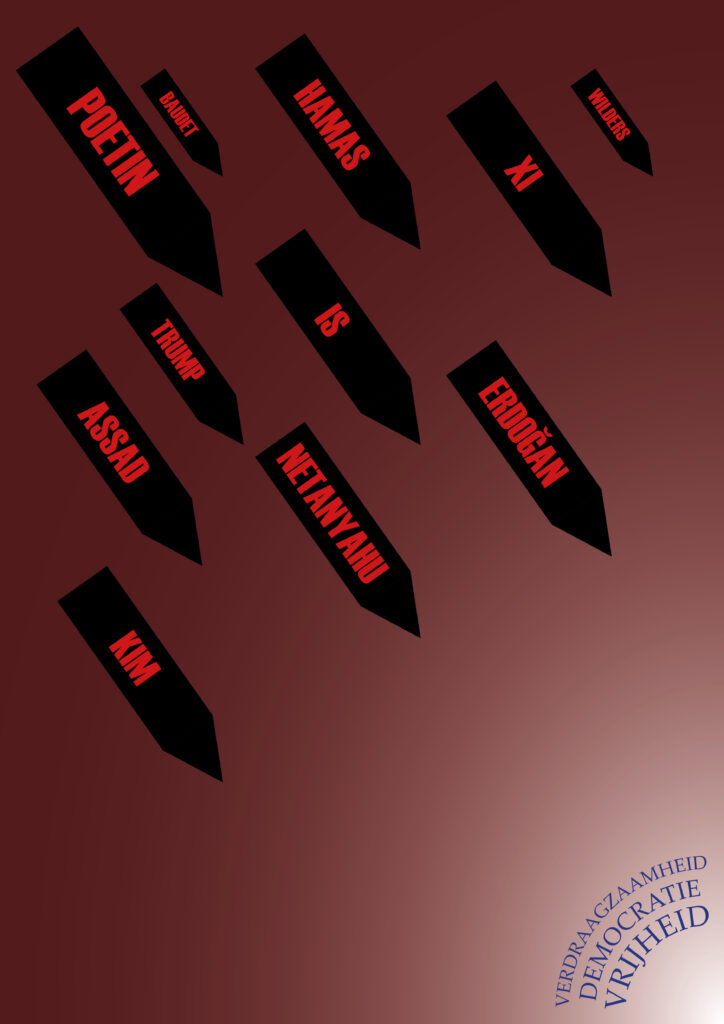
In de eerste versie zie je dat ik de pest heb aan dictators, bijna-dictators en hun vriendjes. Net als Hitler en Mussolini zijn die van nu soms zelfs democratisch gekozen, waarna ze hebben besloten dat ze nooit meer weggaan. Ik heb wel wat getwijfeld wat er op de bommen moet staan. Bijna-dictatorbommen kloppen wel, die bedreigen ons nog, maar actuele dictators als Kim, Poetin, Xi en Assad 2 hadden de vrijheid al verwoest.
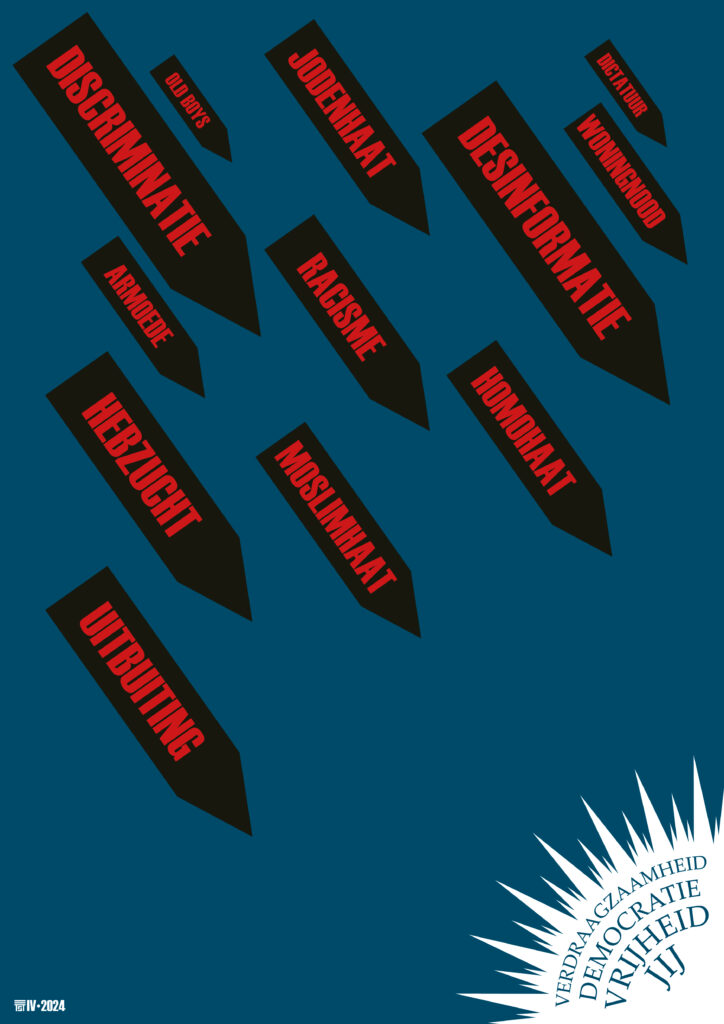
Vandaar een tweede versie met vormen van discriminatie, uitsluiting en ander onrecht op de bommen. We hebben het hier in Nederland allemaal, op de dictatuur na…
De kleur van dit ontwerp is zo dat het kan worden gezeefdrukt in (donker) cyaan en rood. Als je die overlappend afdrukt wordt de kleur zwart. De letter op de bommen is de Haettenschweiler, speciaal vanwege het lelijke woordbeeld. De andere letter is de Palatino.
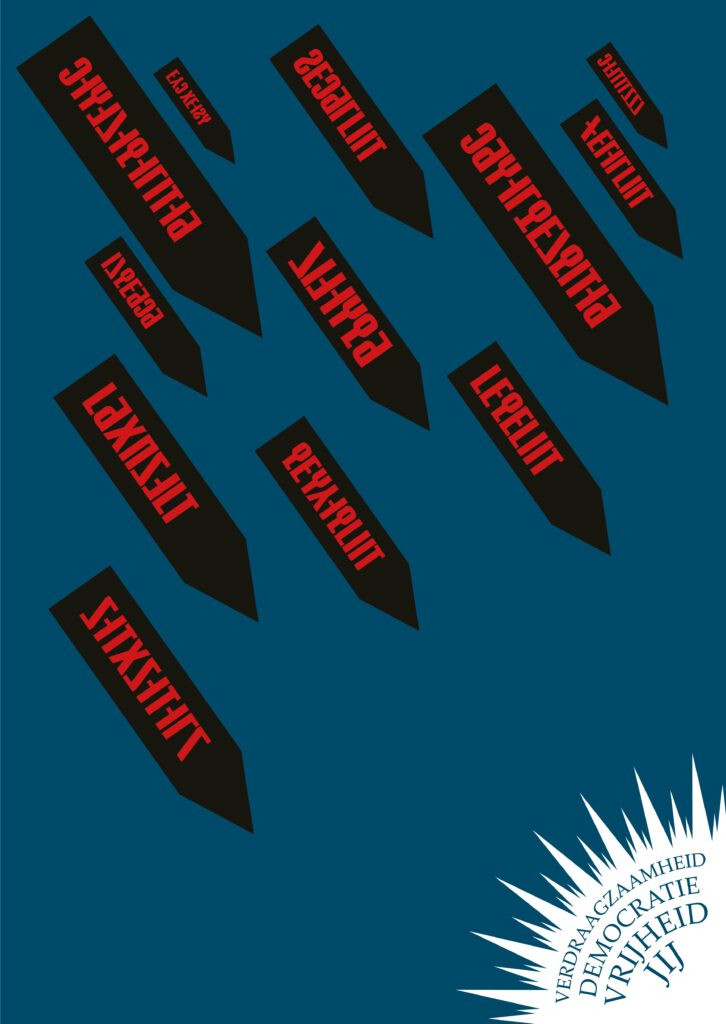
Was dit te concreet, met al die woorden? Moesten de lezers het zelf kunnen bedenken? In juni probeerde ik een versie met onleesbare bommen.
Dat was toch niet zo’n goed idee. Het leek net alsof Armenië onze vrijheid bedreigde.
Ik kwam er niet goed uit totdat de Verenigde Staten werden overgenomen door Trumps kliek …
… en ik een tekst tegenkwam van Martin Niemöller, een Duitse dominee. In 1933 dacht hij nog dat Hitler iets goeds te bieden had, maar geleidelijk aan zag hij in dat de nazi’s niet de gemeenschapsstichters waren die ze beweerden te zijn. Na een preek tegen Hitler in 1937 belandde Niemöller in concentratiekamp Sachsenhausen, en later in Dachau. Hij overleefde de oorlog en overleed in 1984.
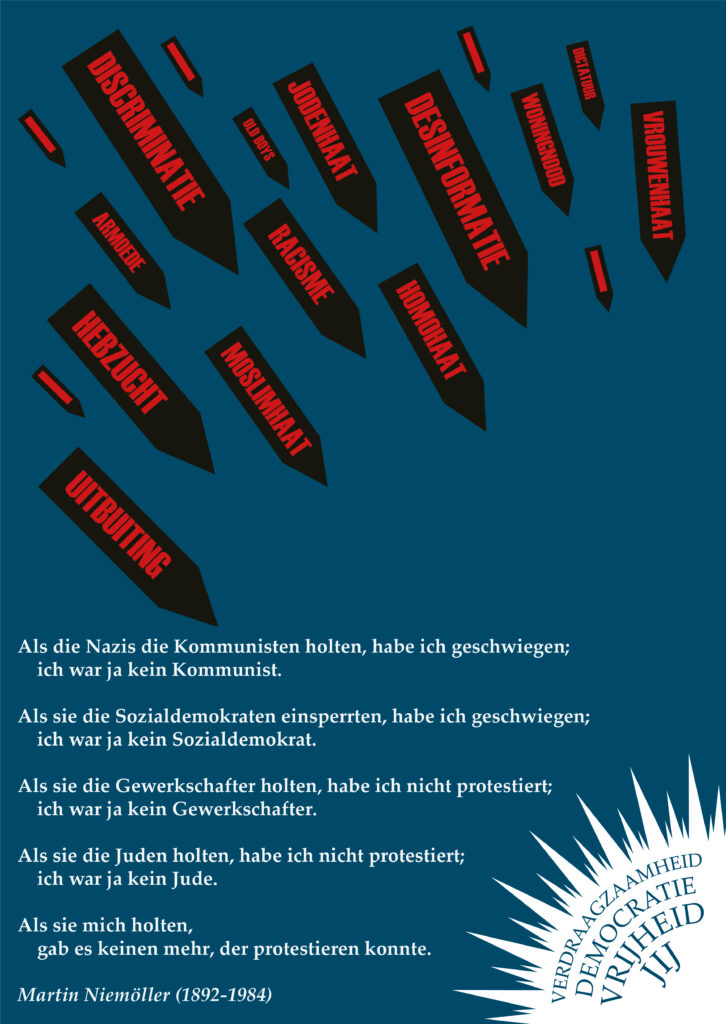
Toen de nazi’s de communisten arresteerden heb ik gezwegen;
ik was immers geen communist.
Toen ze de sociaaldemocraten gevangenzetten heb ik gezwegen;
ik was immers geen sociaaldemocraat.
Toen ze de vakbondslieden kwamen halen heb ik niet geprotesteerd;
ik was immers geen vakbondsman.
Toen ze de Joden opsloten heb ik niet geprotesteerd;
ik was immers geen Jood.
Toen ze mij kwamen halen,
was er niemand meer die nog kon protesteren.
Om na te denken over vrijheid hoef je niet te wachten tot 5 mei.
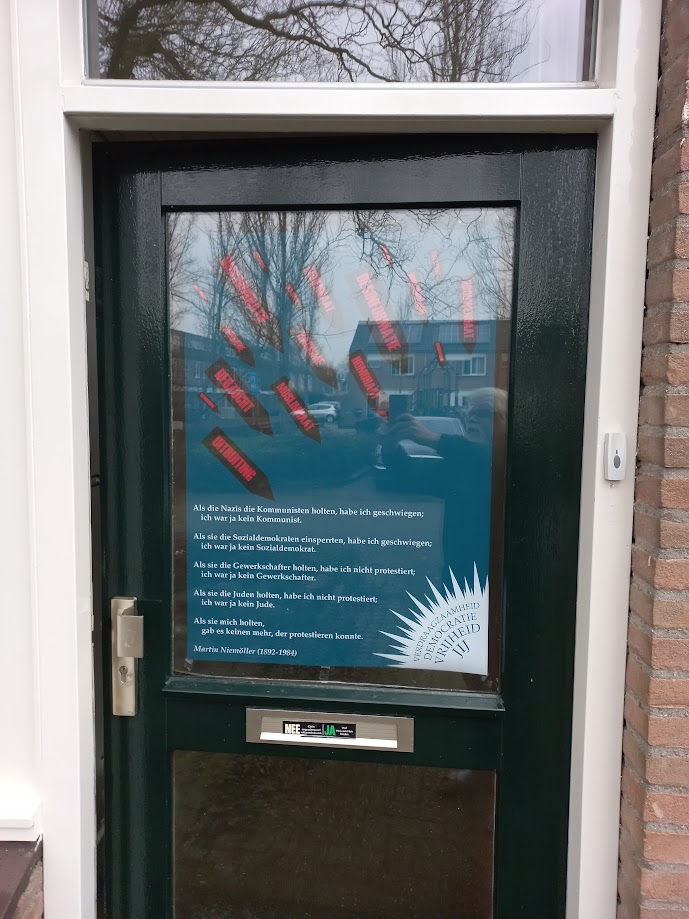
De poster hangt sinds deze vorige week op onze voordeur.